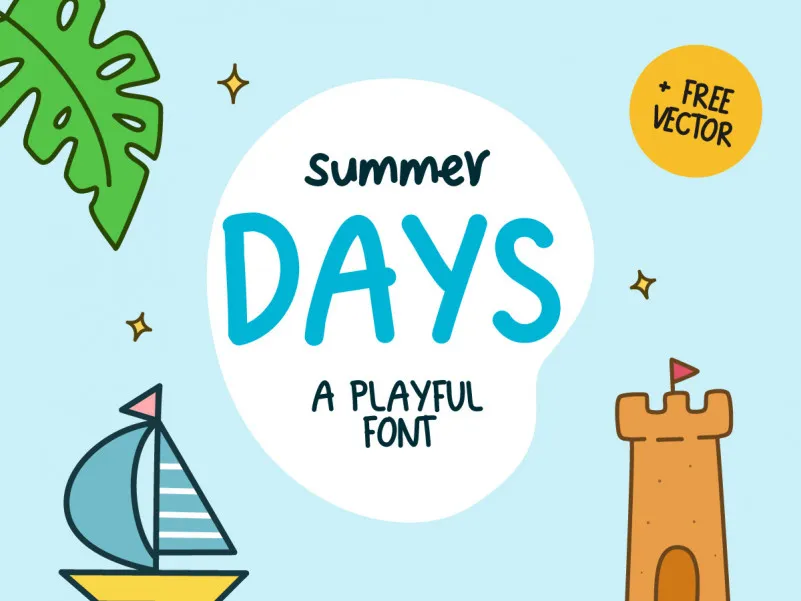
Summer Days Font – Download Grátis
Esta é uma fonte feita à mão que exibe uma aparência alegre e divertida. Ela parece ter sido escrita por alguém com um grande sorriso nos lábios, tornando-a ideal para qualquer projeto criativo. Seu estilo agradável torna esta fonte extremamente versátil, sendo perfeita para múltiplas situações de design. Adicione-a às suas ideias criativas e observe como ela as faz brilhar! Seja você um designer de logotipos, editor de fotos ou qualquer outro tipo de artista visual, esta fonte aprimorará seu trabalho. Ela pode ser usada para criar cartazes em grandes eventos ao ar livre, embutir em uma nova página web ou adicionar um toque único à sua arte digital. A versão ‘Summer Days Font’ da Heloyud é um dos recursos gráficos que você não quer deixar de experimentar.